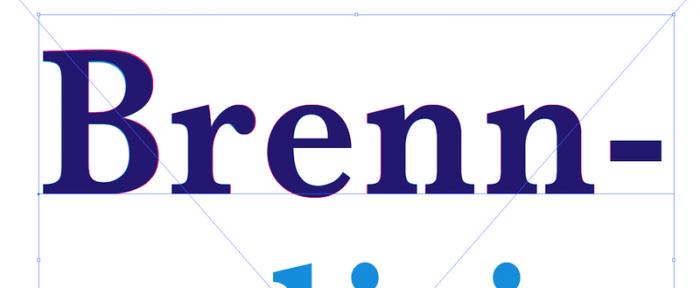
ich suche hilflos nach der in dem Dokument verwendeten Schriftart. Könnt Ihr mir helfen?
Ich tippe auf Baskerville. Du kannst das aber einfach nachprüfen, indem Du Dir die PDF-Eigenschaften im Adobe Acrobat Reader ansiehst. Vielleicht liege ich auch daneben … :-)
Danke Robert, doch leider ist es nicht die Baskerville. Hast du noch eine Idee?
Versuch mal die Baskerville zu stauchen ;)
Ich habe im Moment kaum Zeit, aber hier das Ergebnis bei 90 % Skalierung und Laufweite auf 25:
yep, das Original ist auf 111,145786892555 % in die Höhe verzogen :-)